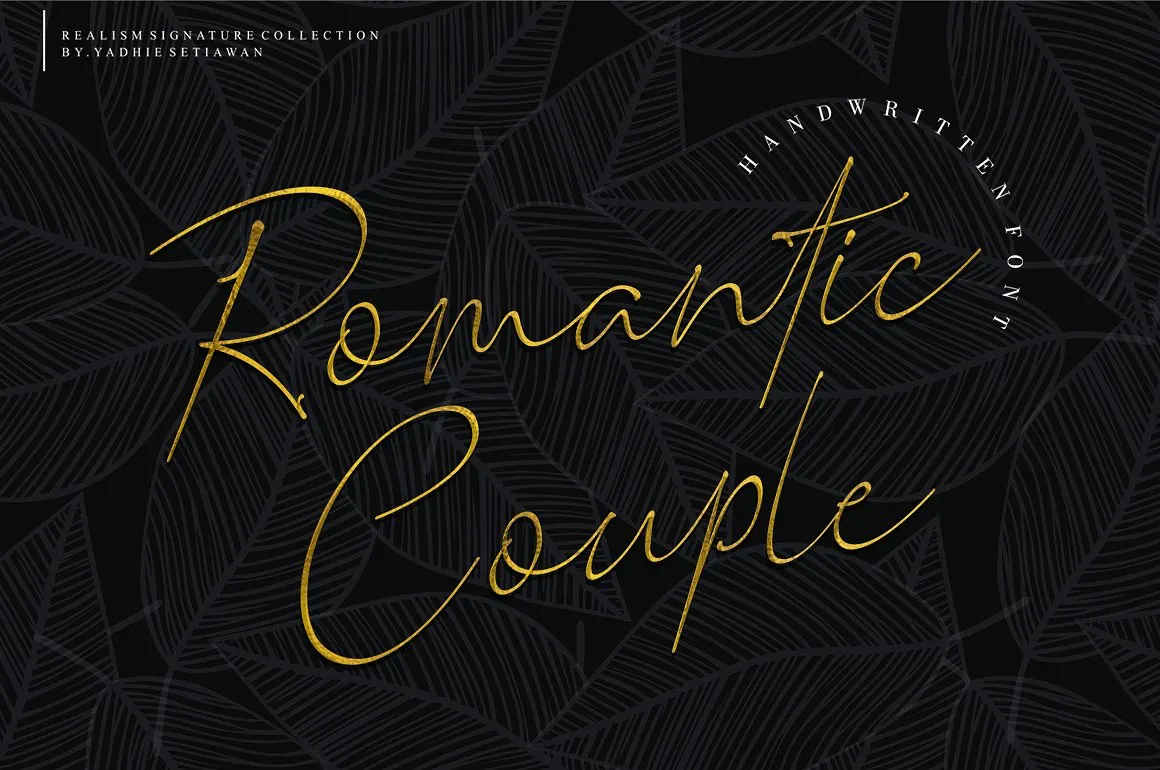
Romantic Couple Handwritten Font – Download Grátis
Introduzimos a Romantico Couple Signature Font, uma fonte premium criada pelo typeline studio para a CreativeMarket. Esta é uma fonte que não apenas oferece beleza e sofisticação ao seu design, mas também transmite um romantismo único que inspira e toca os sentidos. Desenvolvida com o objetivo de criar belas tipografias ou letras, esta fonte Romantico Couple Script atinge um nível notável de realismo, especialmente adequada para aplicações como logotipos pessoais, cartão de visita, marcação de eventos e convites de casamento. Inspirada pela Santorini Font em tons de peaches e creme, a fonte Romantico Couple traz uma atmosfera romântica ao seu design que certamente encantarão seus leitores ou espectadores, seja na web ou em impressos. Não perca esta oportunidade única de adquirir essa bela fonte que irá tornar seus projetos ainda mais personalizados e emocionantes.